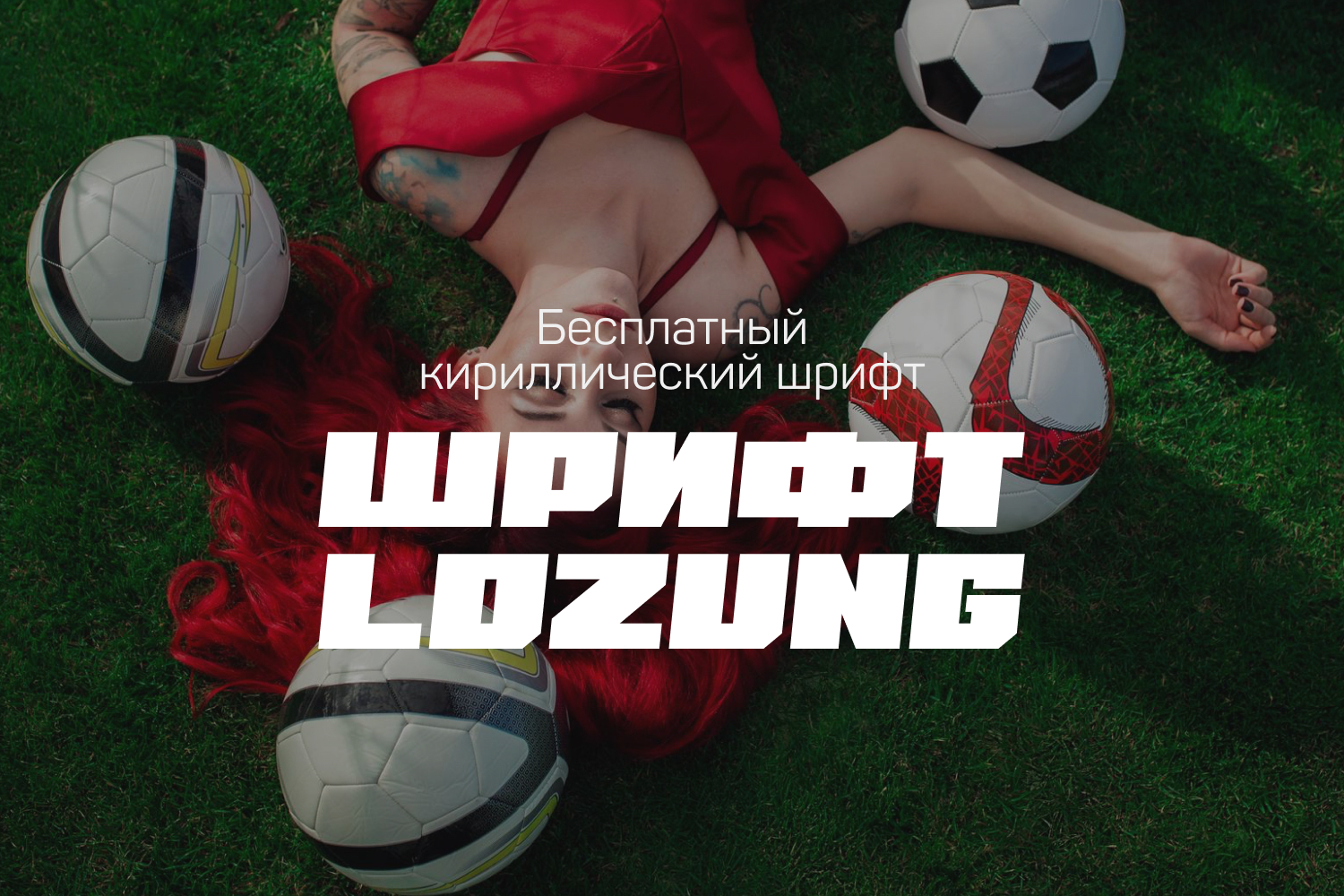
Бесплатный шрифт lozung
Lozung. Мощный, динамичный шрифт. Отлично впишется под спортивные тематики или плакаты. Кто-то, чтобы начать бегать покупает кроссовки. Дизайнеру достаточно установить шрифт 😁 Нам этом данное мероприятие можно и закончить.